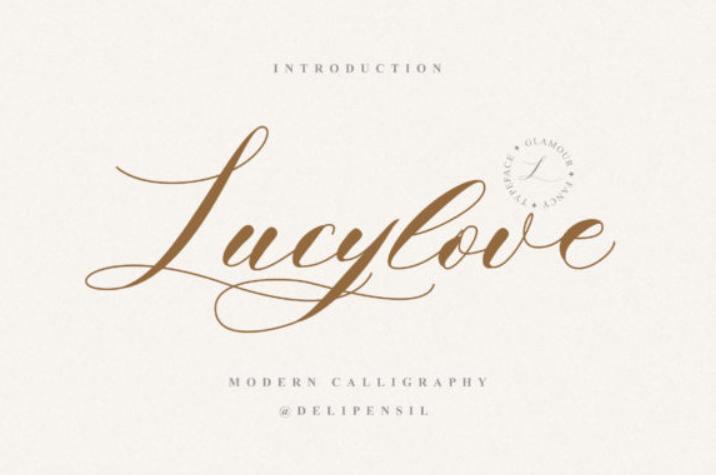
[Creativefabrica] Lucylove Font (delipensil)
Lucylove - прекрасный и неподвластный времени рукописный шрифт. Это лучший выбор для создания привлекательных логотипов, брендов и цитат. Каждая буква имеет уникальный и красивый штрих, который оживит ваш дизайн!